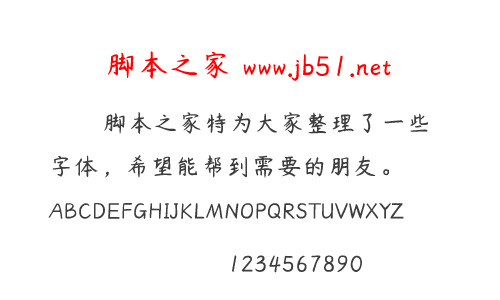
杨任东竹石体-Medium 免费版
杨任东竹石体-Medium是一款杨任东竹石体字体集中的一款中文字体,该字体线条粗细适中,笔画遒劲灵动,连笔张弛有度,结体清丽优美,如诗般优雅洒脱,能够应用于文本装潢、信息展示、网页设计、篆刻制模、数据制作、装潢设计、计算艺术设计、视觉设计、字帖等一切合法应用场景,欢迎大家前来下载使用。